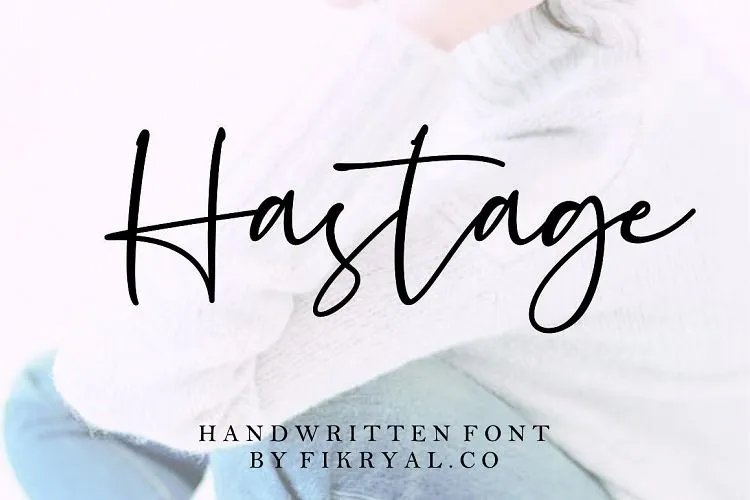
Hastage Handwritten Font
A Hastage Handwritten Font é uma maravilhosa opção para quem busca deixar seu design com um toque pessoal e autêntico. Esta fonte, criada pelo designer fikryal, traz um estilo de escrita à mão que combina elegância e naturalidade numa perfeita harmonia. Perfeita tanto para criações digitais como para impressão, a Hastage Handwritten Font é ideal para aplicação em logotipos, marca identidade, cartas de convite, títulos, designs de casamento, posts nas redes sociais, anúncios, embalagens de produtos, design de produto, selos, fotografia, água-marinha, eventos especiais, revistas e design para web. Com seu fluxo natural e sofisticado, esta fonte atinge desde as mais simples aplicações digitais até aos designs de maior impacto. Seja em uma postagem nas redes sociais que carrega um toque pessoal ou em uma embalagem de produto com a identidade visual da sua marca, a Hastage Handwritten Font é perfeita para deixar seu design mais autêntico e atraente. A fonte é moderna e elegante, oferecendo flexibilidade para que você use em diversos campos, desde publicações online até designs impressos.